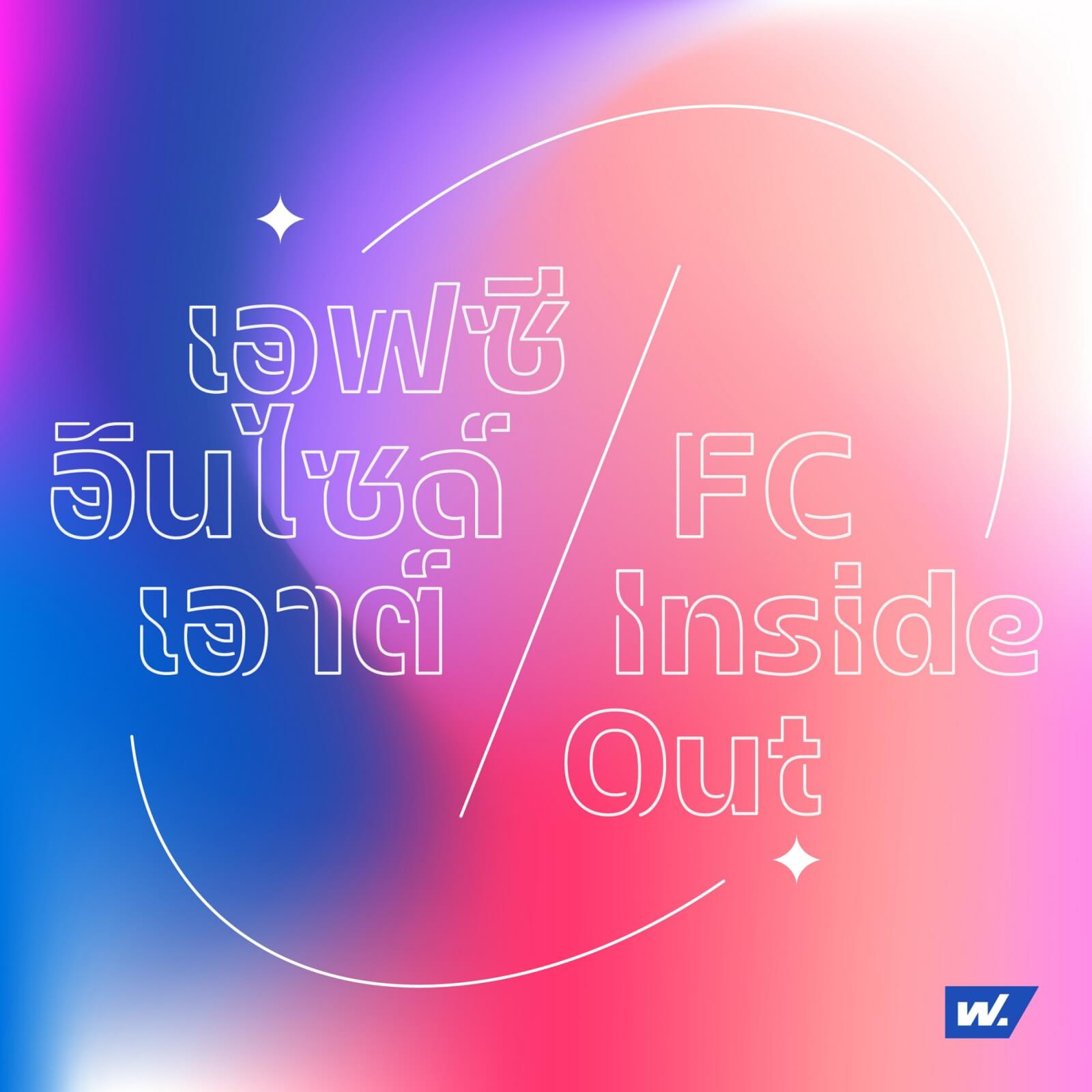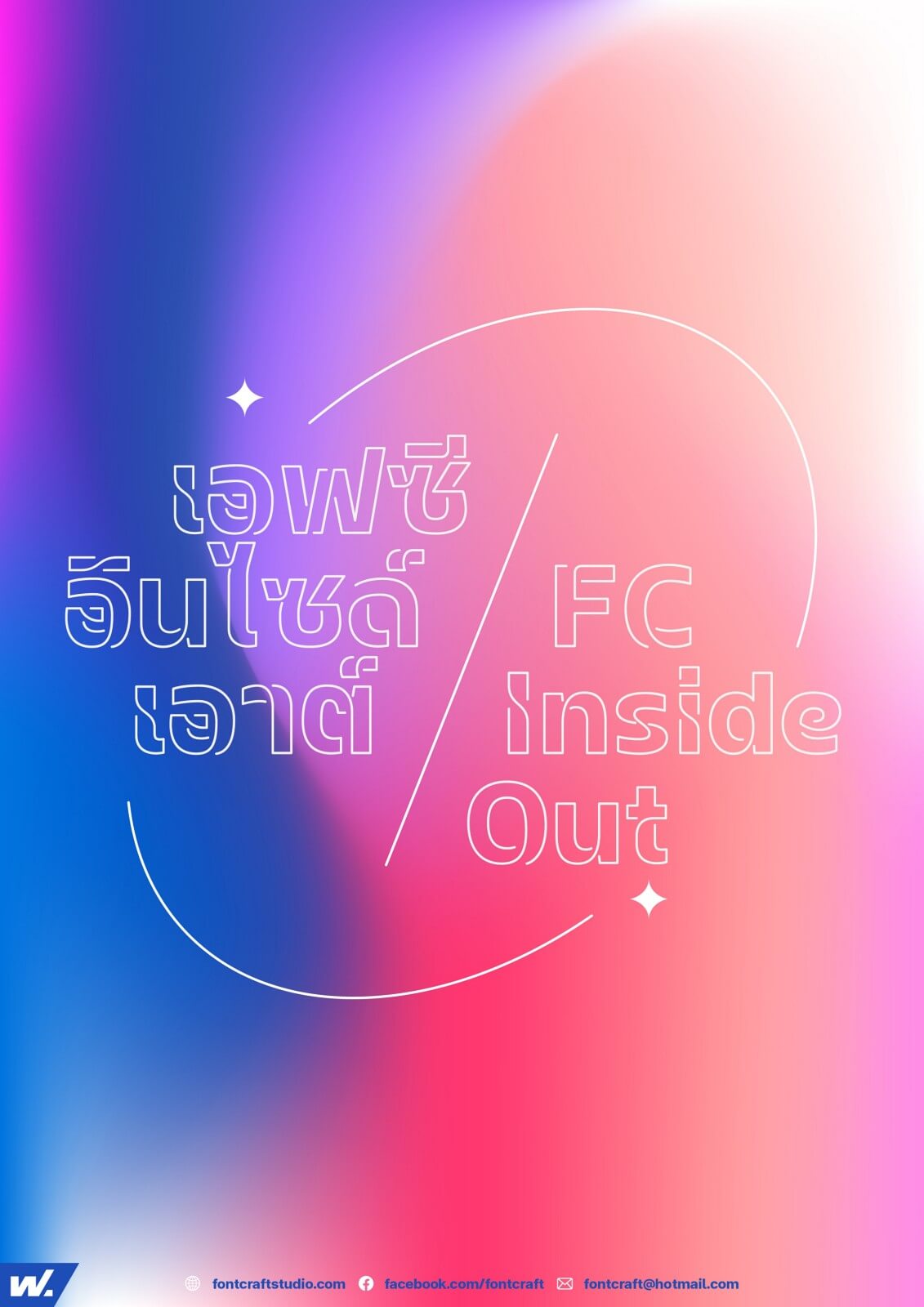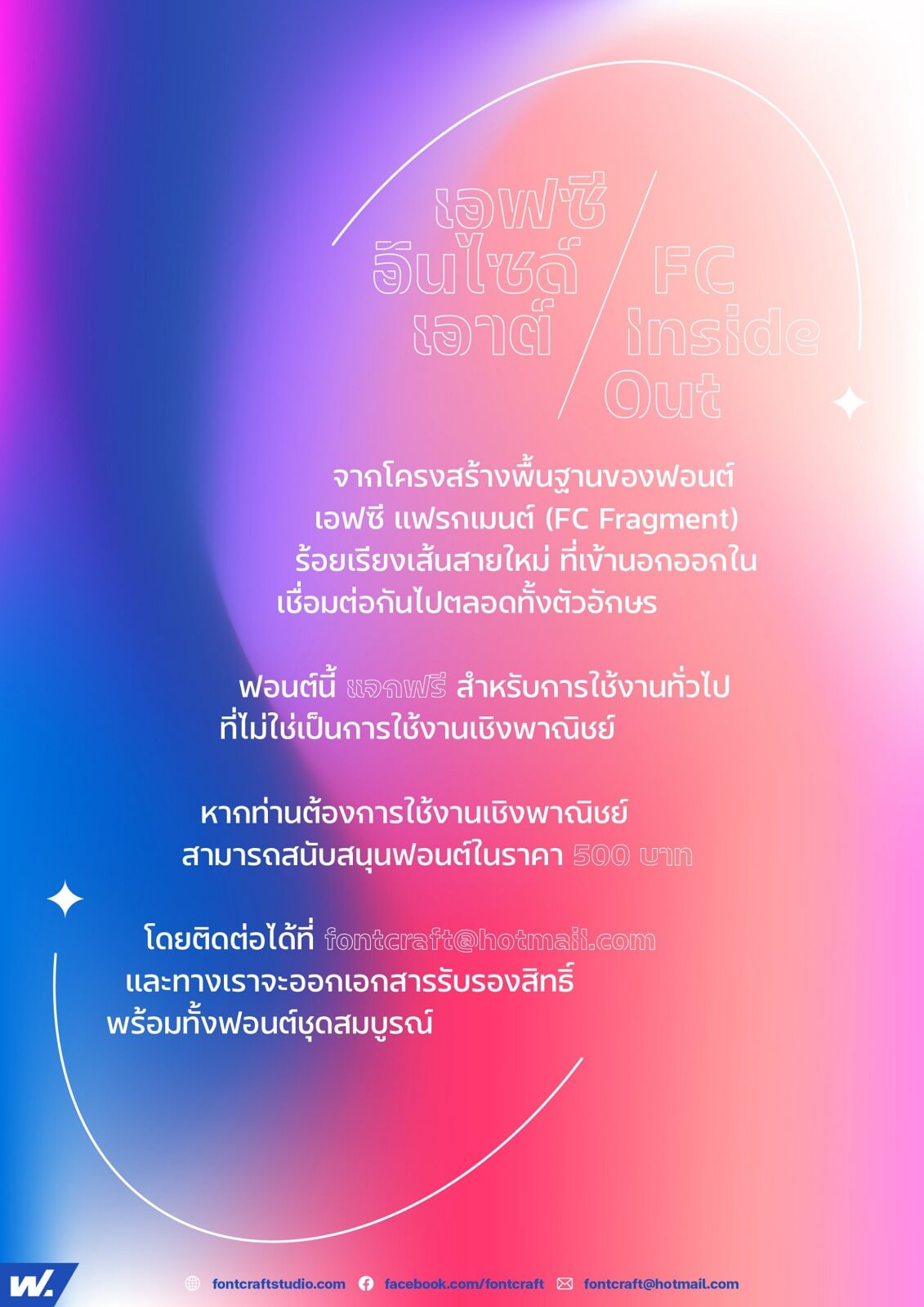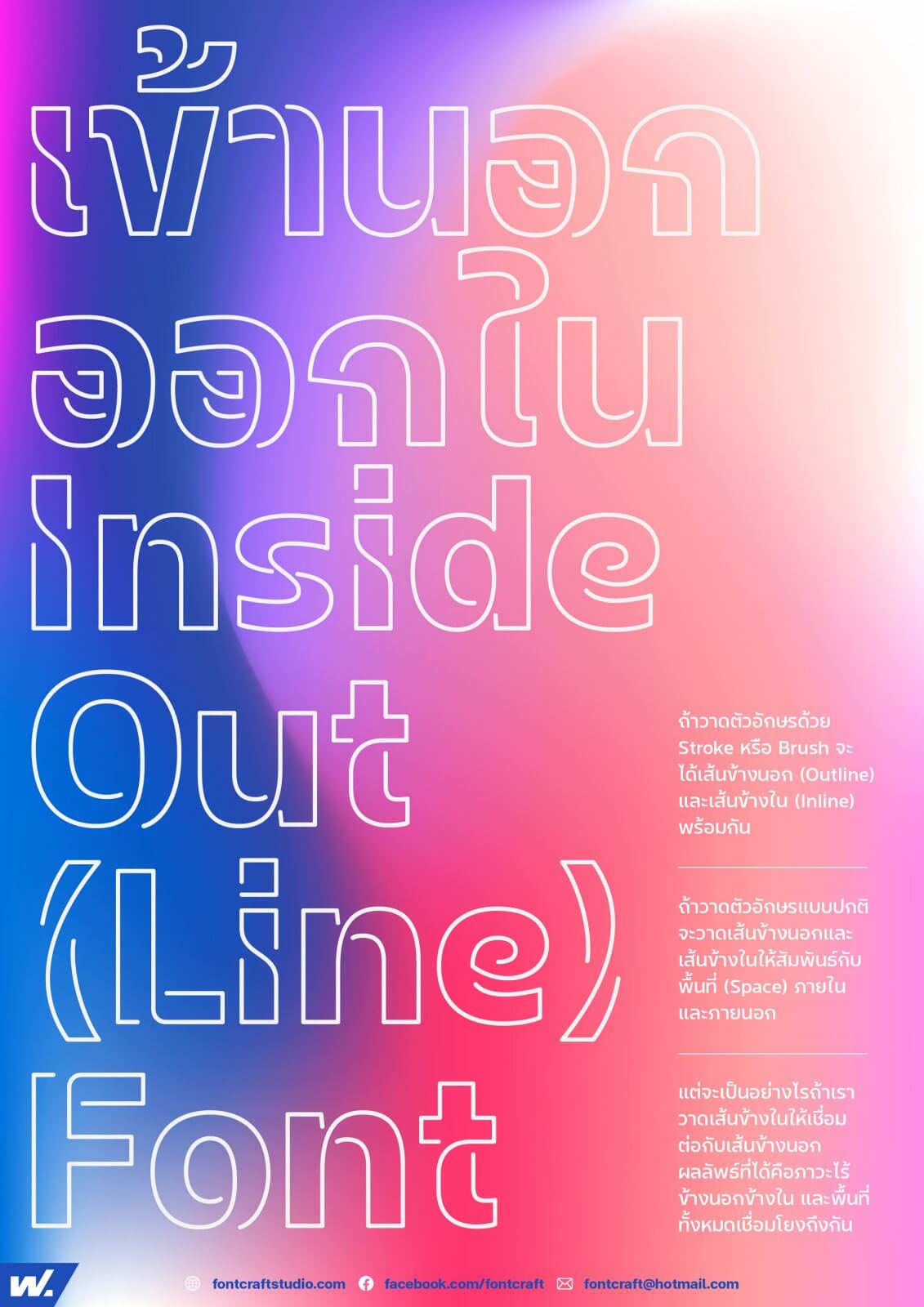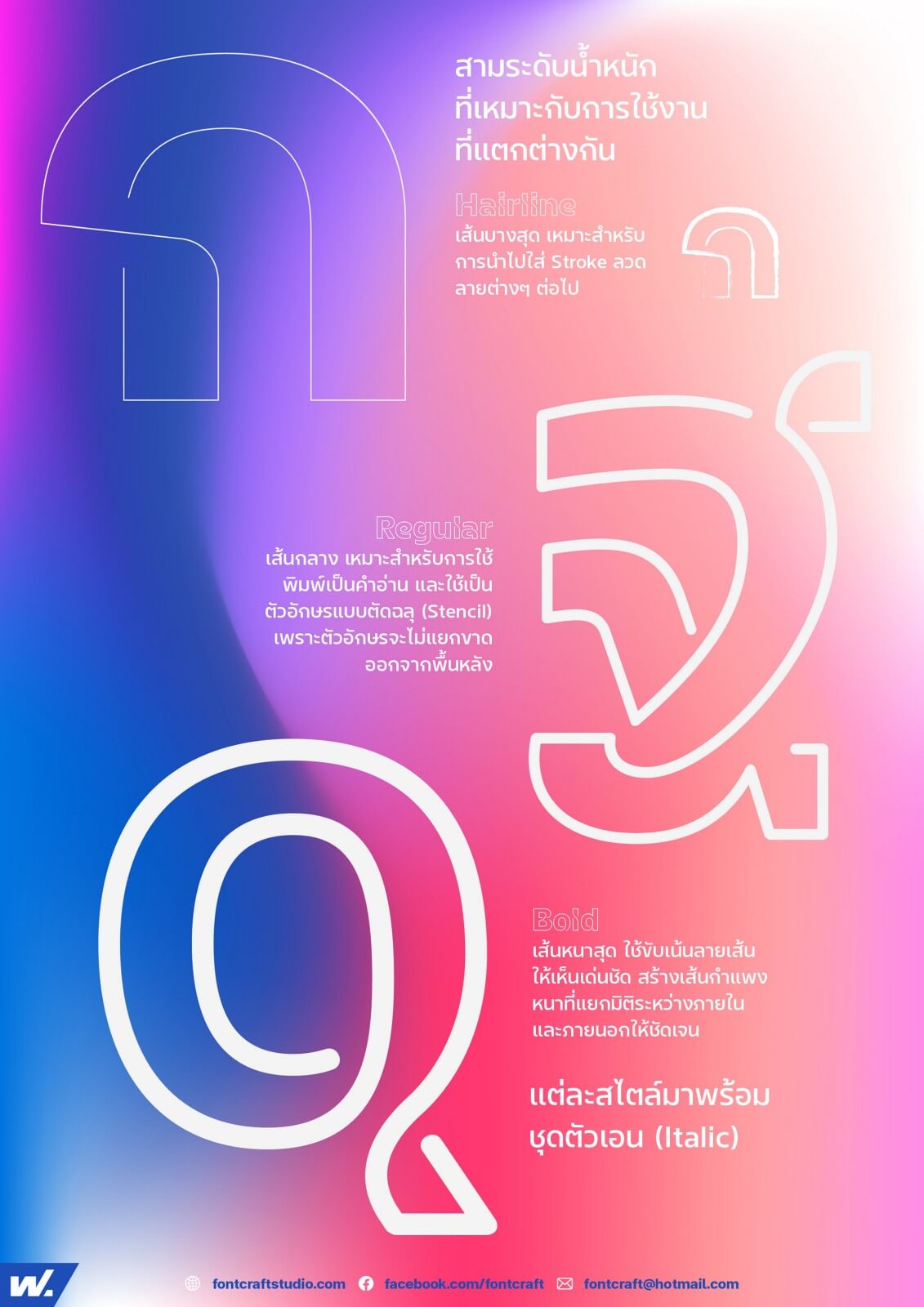
ฟอนต์ที่เข้านอกออกใน Inside Out(Line) Font
จากโครงสร้างพื้นฐานของฟอนต์ เอฟซี แฟรกเมนต์ (FC Fragment) ร้อยเรียงเส้นสายใหม่ ที่เข้านอกออกใน เชื่อมต่อกันไปตลอดทั้งตัวอักษร
โดยทั่วไปถ้าวาดตัวอักษรด้วย Stroke หรือ Brush เราจะได้เส้นข้างนอก (Outline) และเส้นข้างใน (Inline) พร้อมกัน และถ้าวาดตัวอักษรแบบปกติ เราจะวาดเส้นข้างนอกและเส้นข้างในให้สัมพันธ์กับพื้นที่ (Space) ภายในและภายนอก แต่จะเป็นอย่างไรถ้าเราวาดเส้นข้างในให้เชื่อมต่อกับเส้นข้างนอก ผลลัพธ์ที่ได้คือภาวะไร้ข้างนอกข้างใน และพื้นที่ทั้งหมดเชื่อมโยงถึงกัน
ฟอนต์เอฟซี อินไซด์เอาท์ มาในสามระดับน้ำหนักที่เหมาะกับการใช้งานที่แตกต่างกัน
- Hairline – เส้นบางสุด เหมาะสำหรับการนำไปใส่ Stroke ลวดลายต่างๆ ต่อไป
- Regular – เส้นกลาง เหมาะสำหรับการใช้พิมพ์เป็นคำอ่าน และใช้เป็นตัวอักษรแบบตั
- ฉลุ (Stencil) เพราะตัวอักษรจะไม่แยกขาดออกจากพื้นหลัง
- Bold – เส้นหนาสุด ใช้ขับเน้นลายเส้นให้เห็นเด่นชัด สร้างเส้นกำแพงหนาที่แยกมิติระหว่างภายในและภายนอกให้ชัดเจน
- แต่ละสไตล์มาพร้อมชุดตัวเอน (Italic)